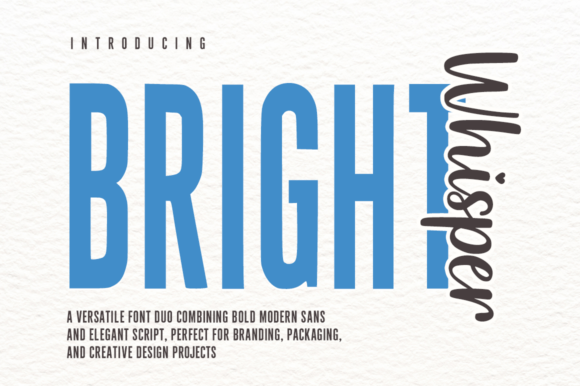
Bright Whisper Duo
Wenn Sie nach hochwertigen Assets wie Bright Whisper Duo suchen, ist dieses Premium-Paket eine fantastische Wahl für Ihre kreativen Projekte.
Egal, ob Sie POD-Produkte (Print on Demand), Hochzeitseinladungen oder Social-Media-Grafiken erstellen, Bright Whisper Duo ist die ideale Wahl.